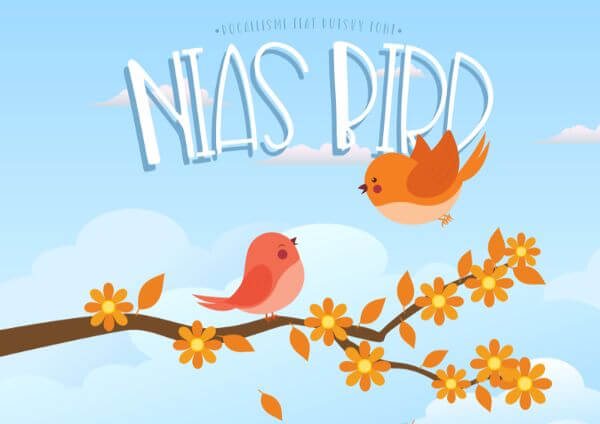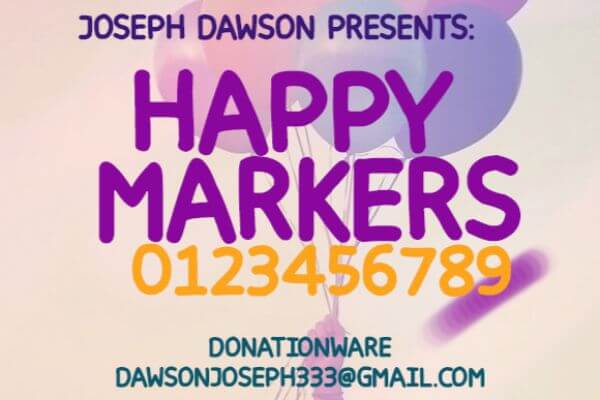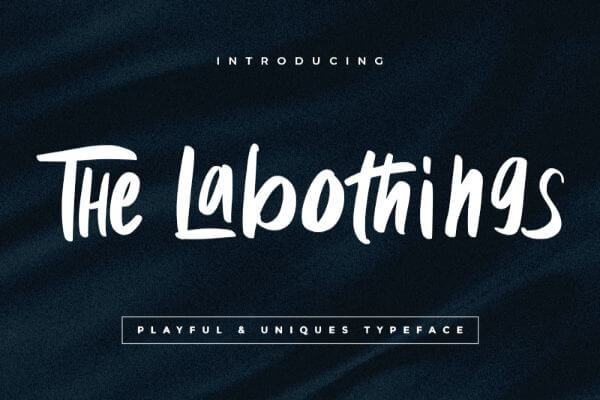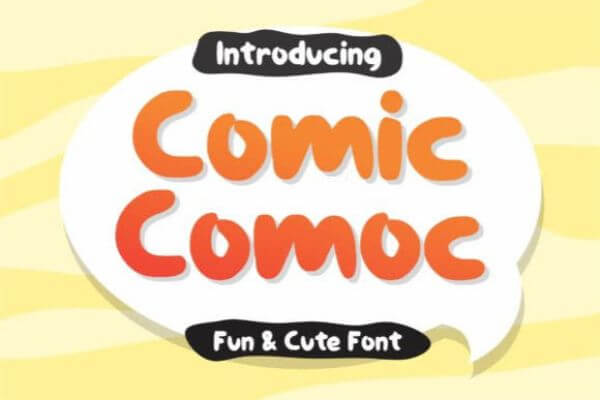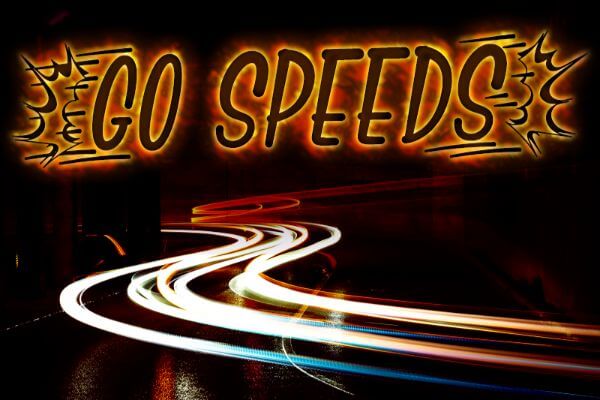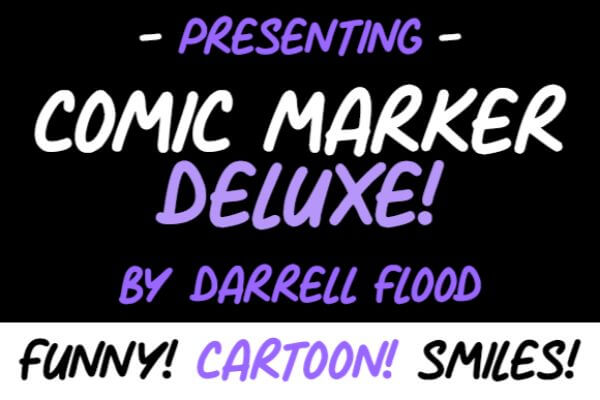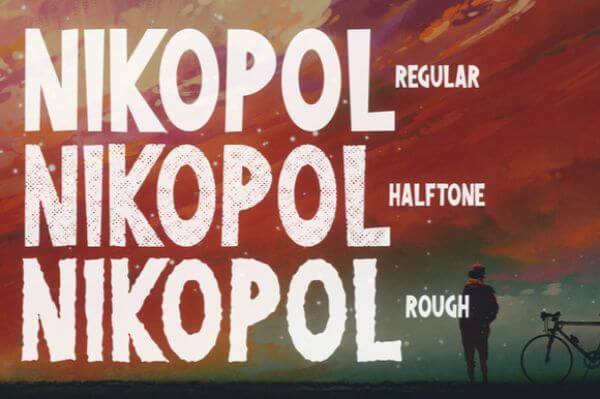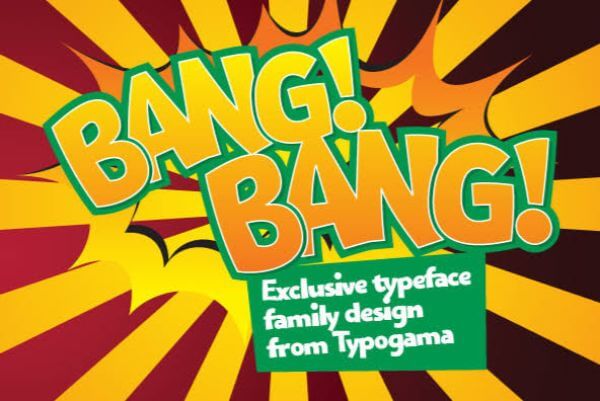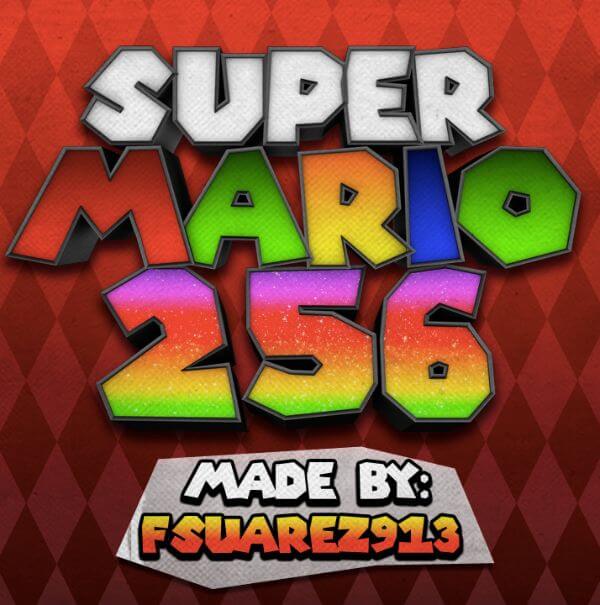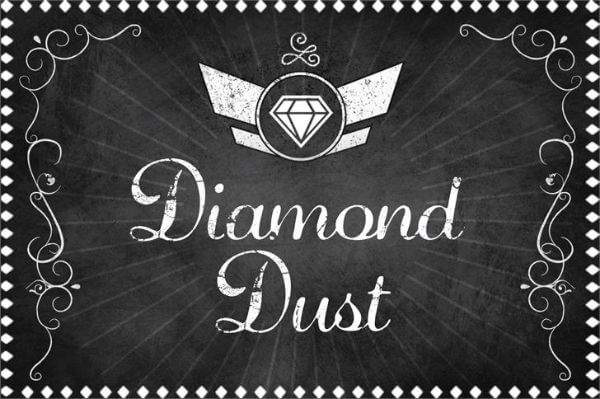
かわいいものからスタイリッシュなものまで!プロジェクトに最適な25の無料コミックフォント
デザイナーには、最新の状態に保つ必要のある設計要素がたくさんあります。 さまざまな要素には、パターン、デザイン手法、配色、およびタイポグラフィも含まれます。 タイポグラフィについて話すとき、1つの重要な要素はフォントです。 フォントは基本的に、書体とピッチ、間隔、サイズなどの他の文字品質とのブレンドです。
一般に、すべてのデザイナーはセリフとサンセリフのフォントの膨大なコレクションを持っています。 ただし、それらすべてが自由に使えるコミックフォントの優れたリポジトリを保持しているわけではありません。 コミックフォントは、特定の場合に対処しなければならない可能性のある市場のさまざまなニーズに応えるフォントです。
通常、楽しいイベントやアニメーション関連のトピックに使用されます。 彼らは主なターゲットとして若い聴衆にアピールする方法で設計され、作成されます。 次のプロジェクトで使用できる無料のコミックフォントがたくさんあります。
次のプロジェクトに使用する必要がある25のベストコミックフォントは次のとおりです。
1. Nias Bird
Nias Birdは、Ryal Docallismeという名前のデザイナーが作成したコミックフォントです。 ユニークで楽しいコミックフォントのようです。 各キャラクターの上半分は下半分より重い。 これが、このフォントを面白くて独特なものにしている理由です。
2. Happy Markers
Happy Markersは、Joseph Dawsonのフォントです。 多くのコミックフォントとは異なり、これはComic Sansから派生したものではありません。 フォントは丸みのある文字を使用し、すべて大文字の文字を含みます。 フォントは、先端が丸い太いマーカーで描かれているように見えます。 イタリック体も付いています。
3. The Labothings
LabothingsはKotak Kuning Studioが作成した手書きのコミックフォントです。 遊び心があり、エネルギッシュなスクリプトフォントのように見えます。 フォントには大文字と小文字の両方のバリエーションがあります。 これは、テキストベースの唯一の文字フォントセットであり、特殊文字や句読点がありません。
4. Reality Check
Hanodedは、Reality Checkという名前のこのフォントを手書きしています。 大きくて大胆なコミック表示フォントです。 大文字はすべて大文字のバリアントですが、小文字セットにはすべて大文字のバリアントの微妙なバリエーションがあります。 曇り効果はこのコミックフォントにエッジを与えます。
5. Comic Comoc
Comic ComocはDumadi Studiosによるフォントです。 コミックをイメージしたキュートで楽しいディスプレイフォントです。 フォントには太いストロークがあり、デザインプロジェクトに魅力的なひねりを加えています。 大文字と小文字の両方のセットがあります。 コミックやヘッダーのデザイン、コミックキャラクターの命名に最適です。 個人利用は無料です。
6. Tootle Play
Tootle Playフォントは、Midfontによるレタリングフォントコミックです。 それは余分な装飾のない非常に基本的なフォントです。 しかし、これこそがこのフォントの最大の特徴です。 フォントはさまざまな側面に使用でき、圧倒的に見えません。 使いやすく魅力的なコミックフォントです。
7. FishFingers Outline
Fishfingersアウトラインは、FishFingersフォントの大きなセットの一部であるコミックアウトラインフォントです。 キャラクターデザインは、下半分に比べて上半分が重いトールフォントを使用しています。 フォントには、標準と軽量のバリアントもあります。 大文字と小文字の両方があります。
8. Go Speeds
Go speedはKotak Kuning Studioによる別のコミックフォントです。 それは背が高くて重いキャラクターを持っています。 文字は、その名前に忠実であり続けるためにわずかにイタリック体になっています。 このフォントは、緊迫感を生み出すのに最適です。 このフォントを使用する理想的な場所は、レーシングゲーム、イベント、ヘッダーなどです。
9. Super Bad Font
Super bad fontは、Eli Shore Productionが作成したコミックフォントです。 手書きのストロークがあり、一定の重みが付いています。 全角文字を使用したフォントです。 ただし、小文字と大文字のフォントは高さが異なります。 その結果、さまざまな組み合わせと、弾力性のある水平でない効果を作成できます。
10. Comic Marker Deluxe
コミックマーカーデラックスは、ダレルフラッドによって作成されたコミックフォントです。 丸いマーカーペンで描いた手書きの文字のようです。 傾斜したデザインで、イタリック体のフォントのように見えます。
11.  La Gilda
La GlidaはWoodcutter Maneroによるコミックフォントです。 キャラクターは背が高くて細いコミックフォントに見えるように設計されています。 それは、切れ目のない線と粗いエッジを持つ文字を持っているので、それは真のコミックフォントです。 これにより、フォントが他のフォントよりも目立つようになります。
12. Kids Magazine
キッズマガジンは、特に若い読者のためにデザインされた素晴らしいコミックフォントです。 それは素晴らしい見出しフォントとして機能します。 フォントは大胆でエネルギッシュです。 Imagexが作成します。 それはうまく定義されている脂肪ストロークを使用しています。
13.  Hey Comic
Hey Comicは、モダンなアプローチの優れたコミックスタイルのフォントです。 フォントは多言語サポートが付属しています。 このフォントは、風変わりで楽しい漫画本のデザインに最適です。 大文字と小文字のほか、特殊文字も含まれています。 さらに、大胆で楽しい書体があり、Khurasanが作成しました。
14. Nikopol
Nikopolはレトロモダンなコミックフォントを持つコミックファミリーフォントです。 さまざまな書体が付属しています。 フォントは文字がユニークに見えるテクスチャードデザインを持っています。 ラフ、レギュラー、ハーフトーンのスタイルが付属しています。
ハーフトーンスタイルは、ヴィンテージの雰囲気に非常に本物に見えます。 一部のキャラクターには、Caps Lockを使用して切り替えることができる代替バージョンがあります。
15. Bang Bang
Bang Bangは素晴らしいコミックスプラッシュフォントです。 魅力的なページやスプラッシュパネルのデザインに最適です。 このフォントには複数の太さオプションがあり、多言語サポートもあります。 これにより、多くのバリエーションを作成し、単一のフォントを使用してさまざまなスタイルの書体を試すことができます。
16. Comic Tantrum
Comic Tantrumは、誰でもタイトルやスプラッシュパネルに使用できる無料のコミックフォントです。 フォントには、文字ごとに多くのラフでユニークなエッジがあります。 非常に用途の広いフォントで、見出し、インフォグラフィック、ポスター、またはWebページにも使用できます。 さらに、要件に合わせてサイズを変更できます。
17. Woodchuck
Woodchuckは、大胆かつ最小限のコミックフォントです。 ヘッダーや漫画のタイトルのデザインに最適です。 フォントには、各文字に黒い輪郭が付いた3D効果があります。 4つのバリアントが付属しています。 薄く、軽く、規則的で大胆です。
大文字と小文字のフォントが付属しており、1000以上の特殊文字をサポートしています。 さらに、多くのラテン語もサポートしています。
18. Super Mario 2
スーパーマリオ2は、任天堂の人気ゲームフランチャイズマリオシリーズから派生したコミックフォントです。 似たようなフォントを使用し、このような人気のあるゲームでテストされているため、その有効性がそこで検証されています。
他とは一線を画す大胆なデザインで、見出しや劇的なタイトルを作成するのに最適です。 このフォントには、小文字のないすべて大文字の文字が含まれています。 さらに、特殊文字も利用できます。
19. Back Issues
バック・イシューは素晴らしいコミック・フォントです。 ランニングスタイルのデザインを採用しており、娯楽コンテンツに最適です。 フォントには、イタリックや太字などのバリエーションがあり、いろいろと試してみることができます。
このフォントは、対話やストーリーの作成に最適です。 それはあなたが本当に漫画を書いたり描写したりするのに使うことができるフォントです。 さらに、それは小文字をサポートしないオールキャップフォントです。
20. Caricature
似顔絵には、コミックフォントの興味深い見方があります。 各キャラクターに似顔絵が付いているので、キャラクターデザインがユニークで、フォントが非常に魅力的で、各キャラクターに個性を与えます。 同じフォントファミリーの一部であると感じながら各文字を異なるようにする詳細な精度は賞賛に値します。
これはアルファベットだけに限らず、数字にも特定の似顔絵が付いています。 さらに、それは使用する楽しいフォントとして出くわし、内容が軽くてオープンである必要がある状況に最も適しています。
21. Jellygurp
Jellygurpには素晴らしいフォントスタイルがあります。 コンテンツをリフレッシュして魅力的に見せるために役立ちます。 フォントはレイヤーで使用できるようにサポートされているため、このフォントを使用して書体の組み合わせをいじってデザインする際に非常に柔軟性があります。 さらに、フォントには大文字と小文字のセットと2重文字も含まれています。
24. Sketchy Comic
このフォント自体の名前は、コミックフォントであることを反映しています。 Sketchyコミックは、スケッチ愛好家に最適なコミックフォントです。 このフォントの各文字には、個人的なタッチを与えるスケッチの感覚があります。 ヘッダーの作成やバナーのデザインに最適なオールキャップフォントです。
特殊文字や小文字のサポートはありません。 ただし、アルファベット文字だけに使用する場合は、優れたフォントです。
25. Bubble & Soft
バブル&ソフトは、かわいいコミックの書体です。 それは世界中の多くのデザイナーによって使用されているフォントです。 フォントには、次のようなさまざまなウェイトオプションがあります。 標準、標準、拡張、圧縮、イタリック。 フォントはデザインが規則的でシンプルです。 ただし、影響を与える可能性は非常に高くなります。